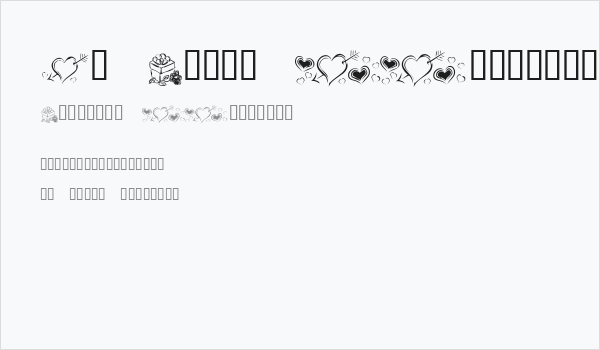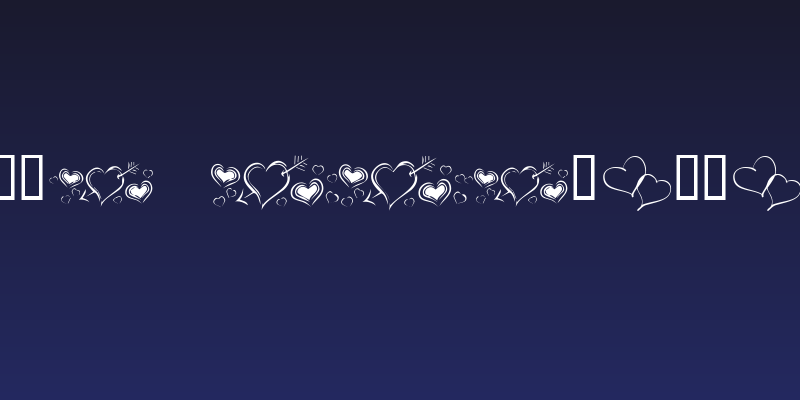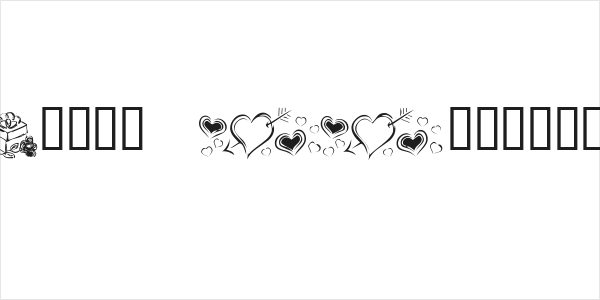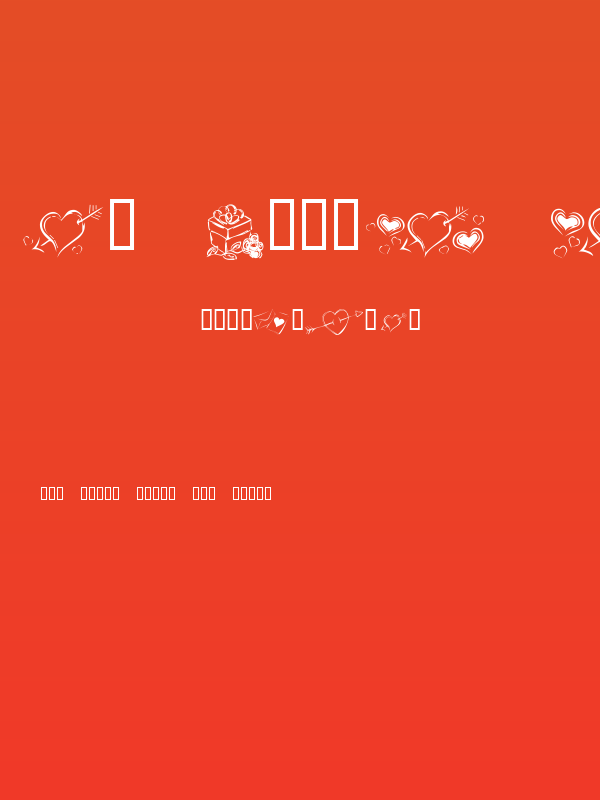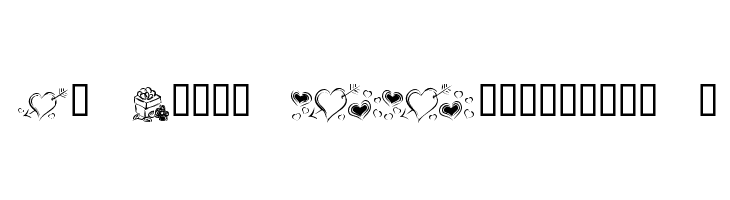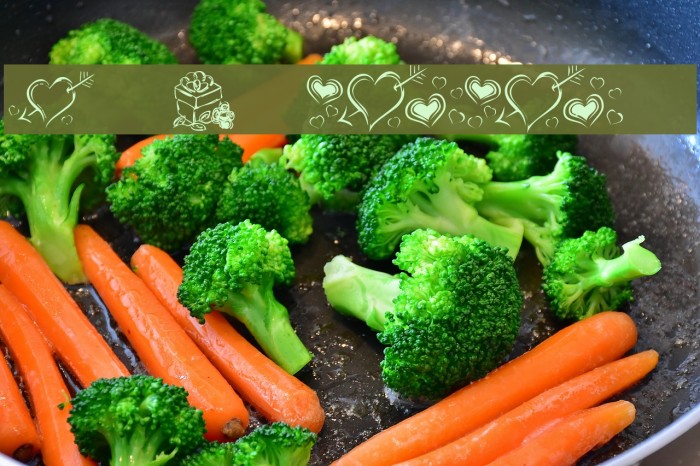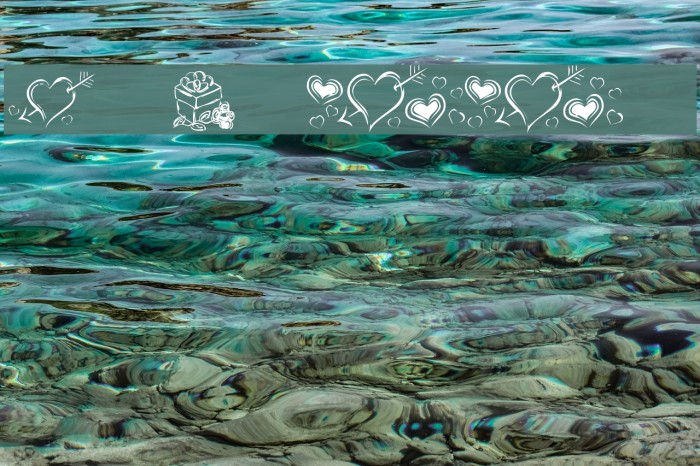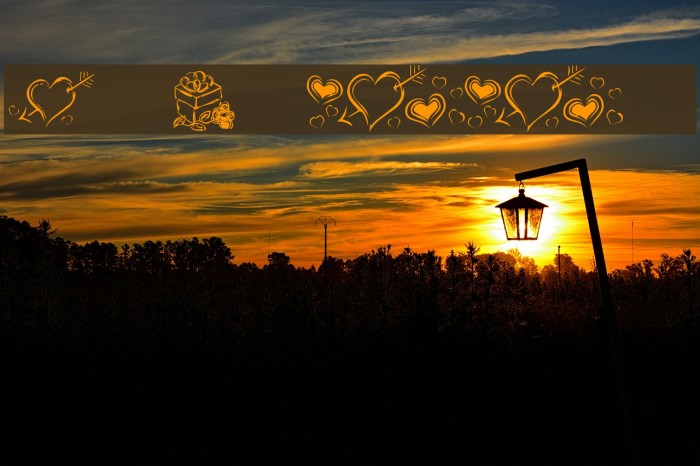
KR Cuori Divertenti 7 Font
✎ Valentine
| Cas d'utilisation | Logos, Decorative elements |
| Projets proposés | Ideal for Valentine's Day cards, wedding invitations, romantic event posters, and playful graphic design projects. |